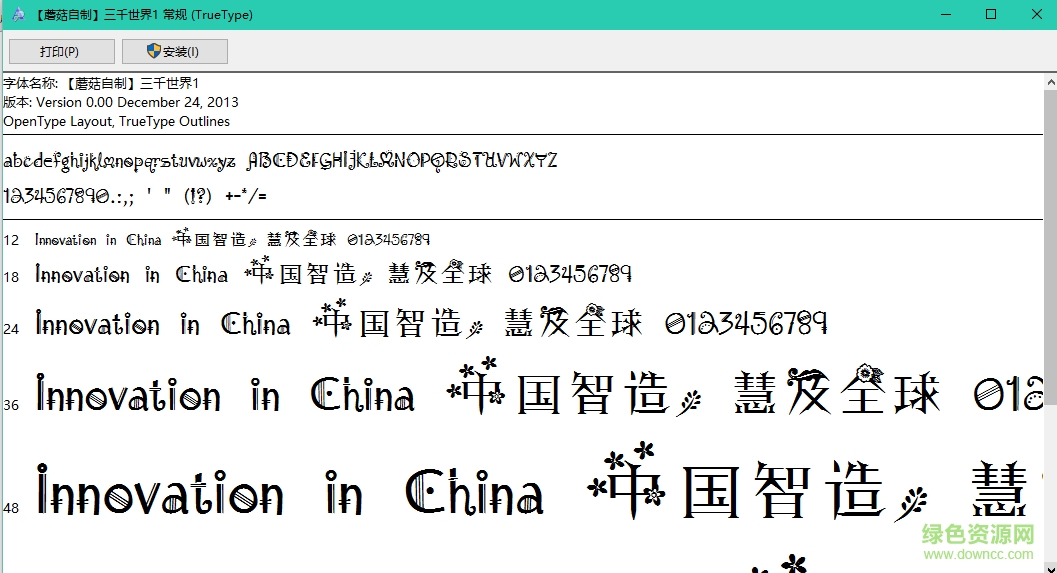
三千世界字體是一款韻味十足的字體,設(shè)計(jì)靈感來(lái)源于佛學(xué),字形非常漂亮,正直剛毅。字體安裝簡(jiǎn)單,在各類廣告設(shè)計(jì)、網(wǎng)頁(yè)設(shè)計(jì)、外包裝設(shè)計(jì)等領(lǐng)域可以運(yùn)用,給受眾心曠神怡的感覺(jué),有興趣的快來(lái)綠色資源網(wǎng)下載體驗(yàn)吧!